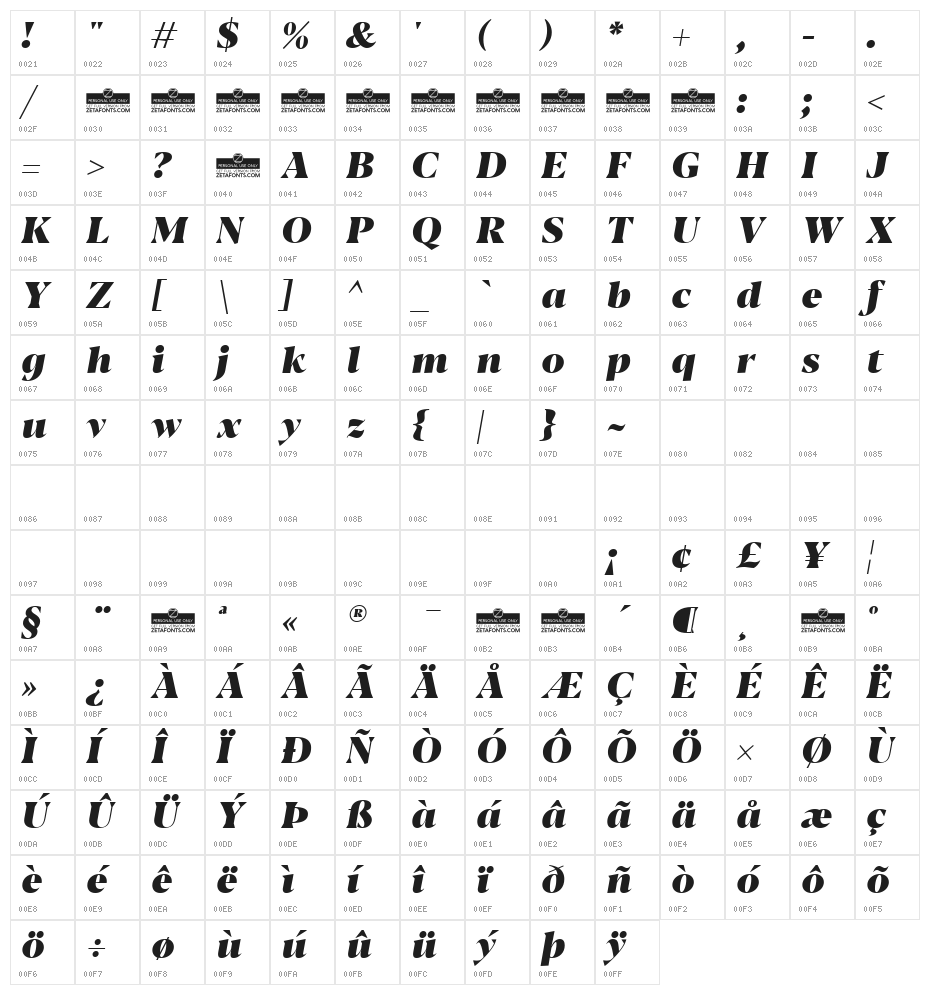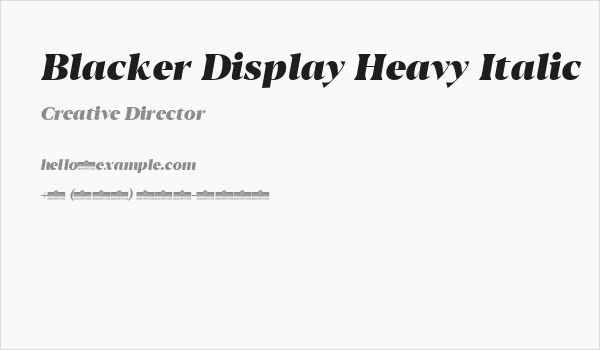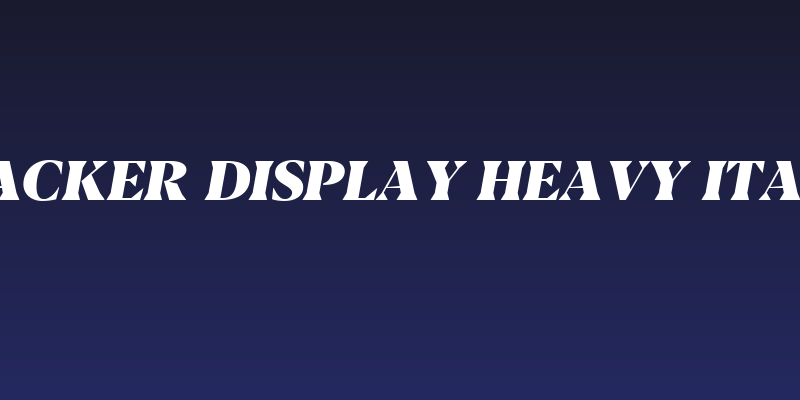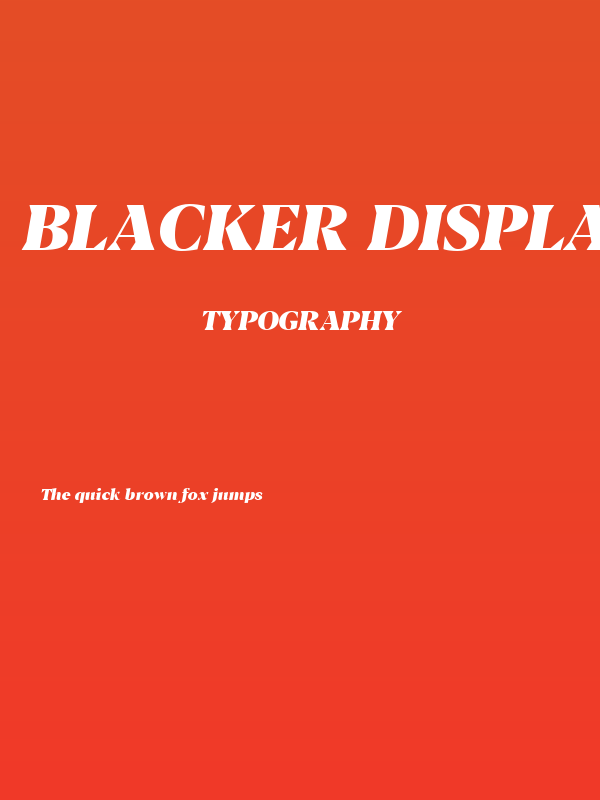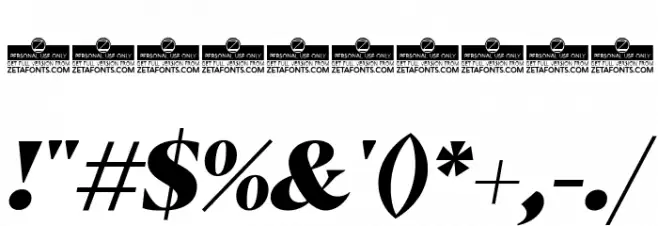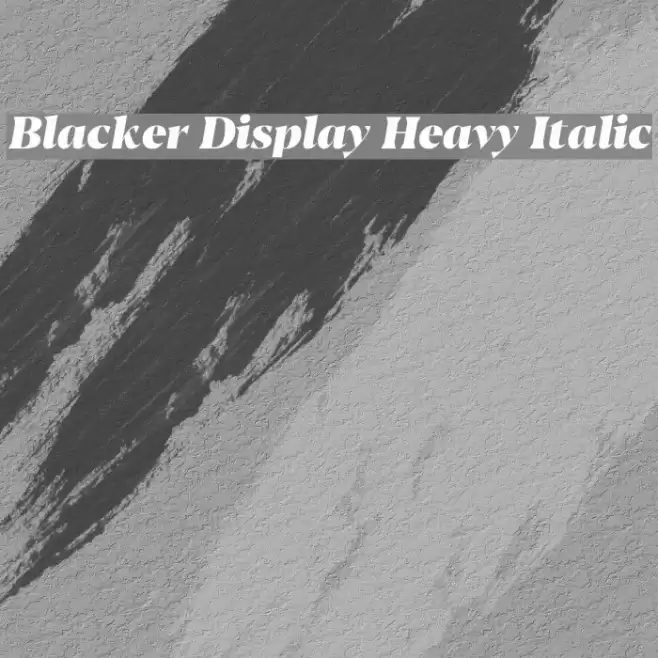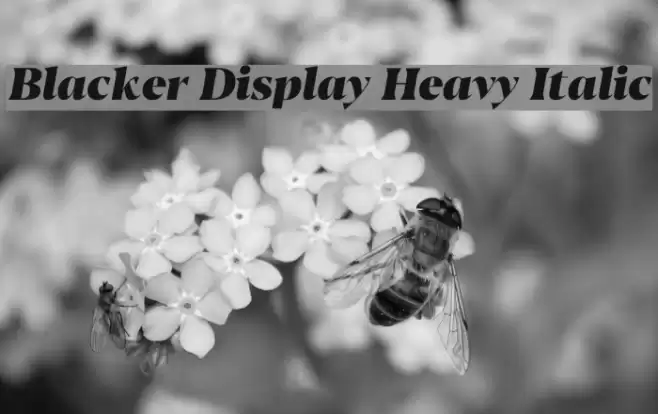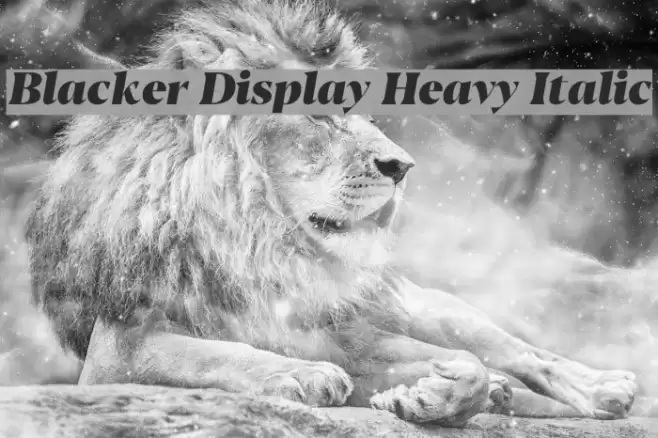
Blacker Display Heavy Italic Font
| Proyectos propuestos | Ideal for headlines, branding, advertising, and editorial design where a strong visual impact is desired. |